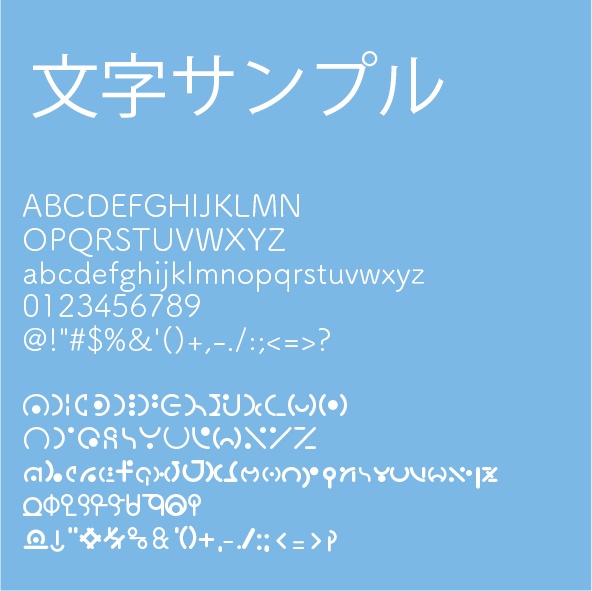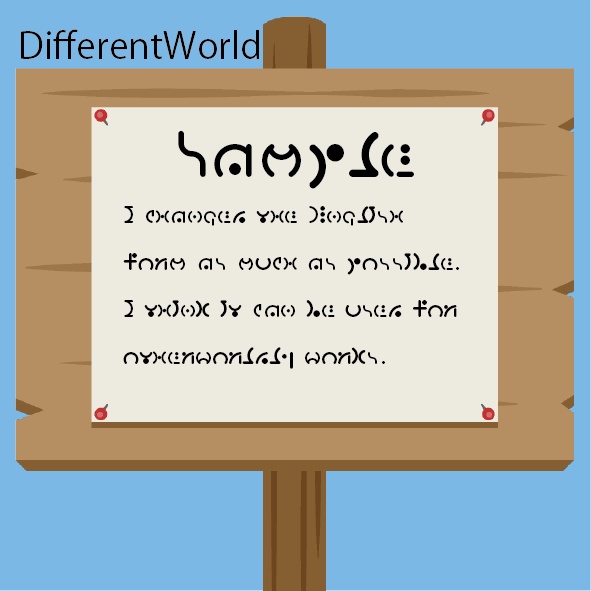
異世界フォント
・はじめに、画像をご覧になった様に可読性はほとんどありません。 ・対応している言語は英語です。 ・初めてフォントを作りました。至らぬ点もあると思いますがご了承ください。 ・またこのデータファイルを販売するのは初めてです。大丈夫だとは思いますが、何かの不具合でデータがうまく取得できない場合は、すぐにご連絡下さい。早急に対応します。 (宣伝していただけると嬉しいです!)
異世界作品にて、日本語や英語が出てくるのが個人的に疑問に思い制作したフォントです。 英語をこの文字に変換するだけで異世界の文字に見えるので、ファンタジー作品を作る際に便利かと思います。数字や記号など、必要最低限はあるかと思います。